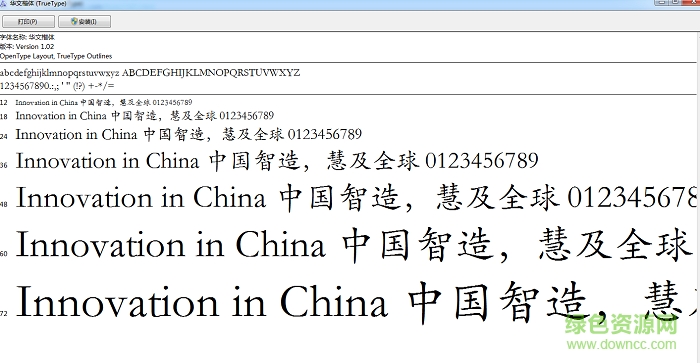
楷體 regular
楷體regular字體是一款方潤(rùn)整齊的標(biāo)準(zhǔn)楷書字體,該字體結(jié)構(gòu)疏密得當(dāng),筆畫挺秀,結(jié)體平穩(wěn),具有良好的可讀性與辨識(shí)度,可以廣泛應(yīng)用于各個(gè)領(lǐng)域,有需要者歡迎免費(fèi)到綠色資源網(wǎng)下載!
楷書四大家介紹
唐柳公權(quán)(柳體)
元趙孟頫(趙體
唐歐陽(yáng)詢(歐體)
唐顏真卿(顏體)
楷體 regular
小楷字體介紹
小楷,顧名思義,是楷書之小者,創(chuàng)始于三國(guó)魏時(shí)的鐘繇。他原是位隸書最杰出的權(quán)威大家,所作楷書的筆意,亦脫胎于漢隸,筆勢(shì)恍如飛鴻戲海,極生動(dòng)之致。惟結(jié)體寬扁,橫畫長(zhǎng)而直畫短,仍存隸分的遺意,然已備盡楷法,實(shí)為正書之祖。到了東晉王羲之,將小楷書法更加以悉心鉆研,使之達(dá)到了盡善盡美的境界,亦奠立了中國(guó)小楷書法優(yōu)美的欣賞標(biāo)準(zhǔn)。